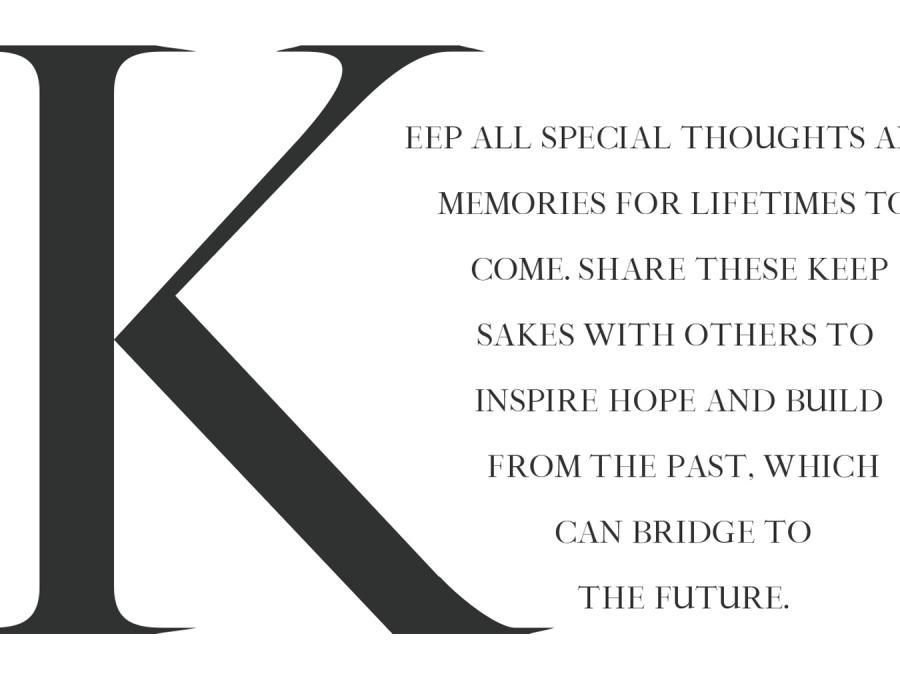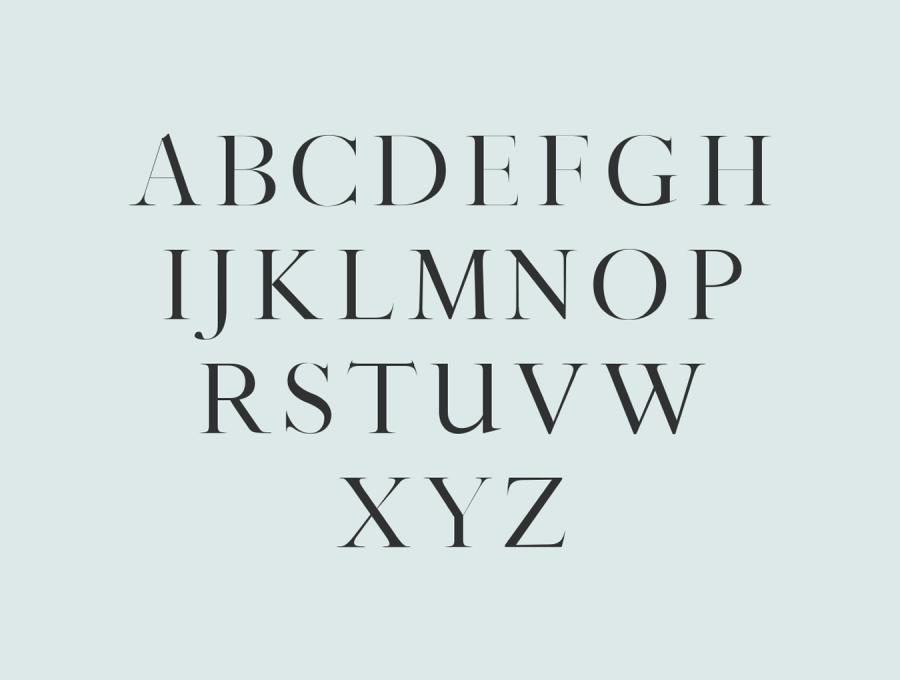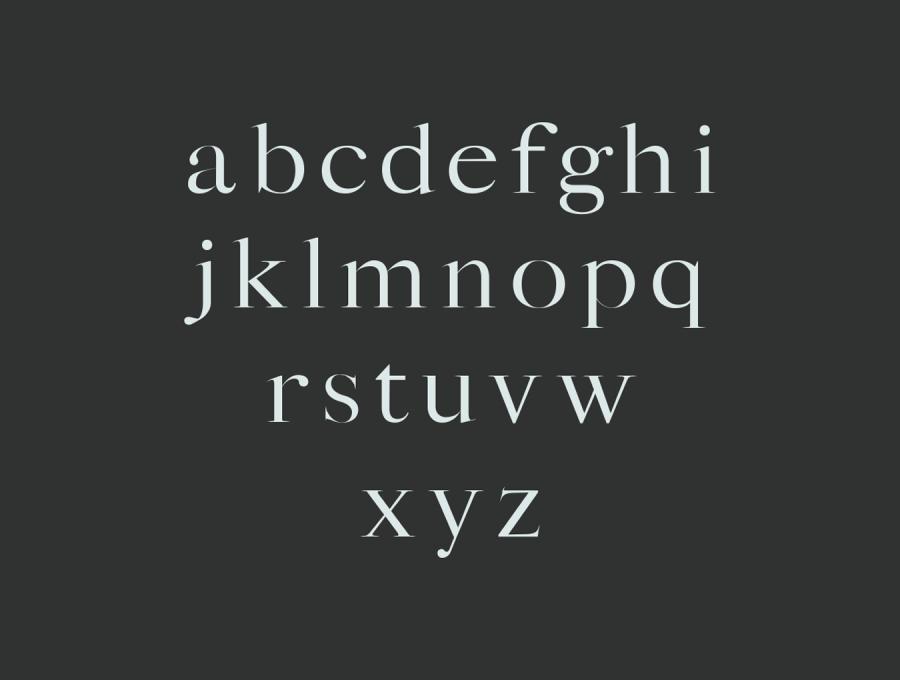
Sharis Serif 英文字体 (Sharis Serif Typeface )
Sharis Serif Typeface 是一个独特的简洁干净的衬线字体系列,其中包含7个重量,Sharis具有独特和现代衬线的外观和感觉。 它是完美的华丽的标志,标题,网页布局,时尚杂志和品牌。 如果你想尝试一个优雅的外观,或者以一个完全永恒的东西,以资本和小写字母为自己的美丽,它在所有的场合上看起来都很漂亮。